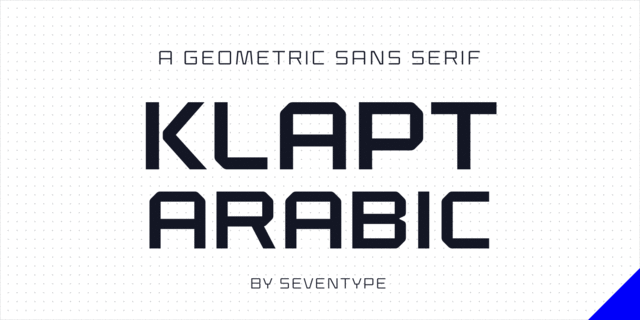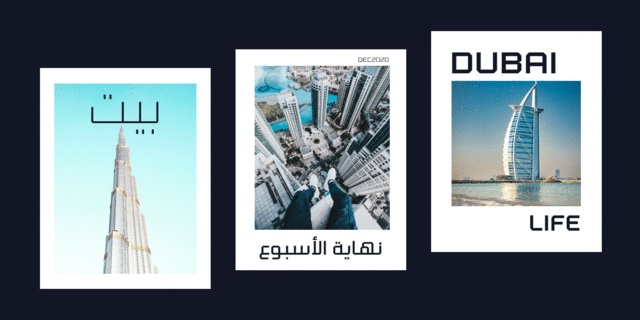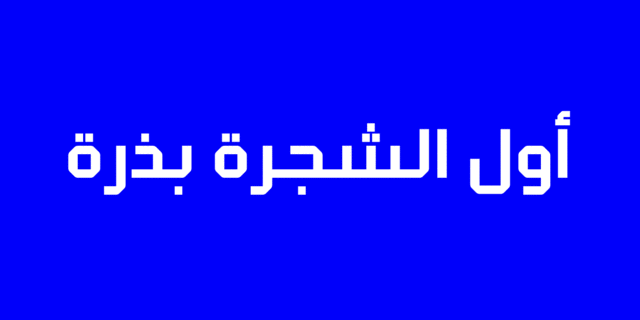
Геометрический гротеск, смягченный снаружи и острый внутри. Обновленное и дополненное поддержкой арабского языка семейство включает расширенный набор символов, поддерживает большинство языков на латинице, и даже вьетнамский! Klapt, который может быть и жирным и очень тонким, предназначен для различного дизайна, от брендинга и фирменного стиля до многостраничных изданий для печати и экранов. Он отлично подходит для акциденции, особенно для заголовков, постеров, журналов, обложек, логотипов. Не стесняйтесь делиться своими дизайнами с использованием Klapt или просто свяжитесь с автором . Шрифт разработала Витория Невес в 2020 году.
Ассоциации c начертанием Klapt Arabic RegularКачества и характер:
ровный, квадратный, точный, логичный, холодный, автоматический, техногенный, твердый, статичный, резкий, четкий, устойчивый, стабильный, тонкий, прямоугольный, городской, современный, машинный, острый, инженерный, урбанистический, чертежный, простой, надежный, уверенный, стальной, космический, безразличный, равнодушный, футуристичный, граненый